字体不是孤独的生物。他们喜欢闲逛,而要确保他们在一起玩得很好。
选择字体就像穿衣服出去玩一样。如果您要去看歌剧,选择非常简单。但是有时您会被邀请到一家米其林星级餐厅/压路机溜冰场,而选择却变得不太明确。
关键是弄清楚信息和受众。一旦确定了这两件事,就可以开始完善选择。
实际选择完美字体的技巧可能有些棘手,并且因设计师而异,但在唯一重要的是字体是否适合该消息。
印刷字体入门
在本指南中,我们将使用几个术语,可能会
第一个是字体和字体之间的区别。虽然通常可以互换使用,但实际上它们并不是一回事。
字体是指一组总体字体。例如,Times New Roman是一种字体。但是,如果您要使用字体的粗体或斜体版本,则为 font 。因此,例如,Times New Roman Bold是一种字体。
类型分类是基于字体外观的一类字体。一些分类包括:
这些只是您可以在各种类型的网站,代工厂等上找到的类型类别。
字体的最常见分类之一是衬线与无衬线。不知道有什么区别?衬线字体的字母尖处有细线。 sans-serif字体没有任何扩展功能。
超家族是一组字体,它们根据不同的类别进行分类。字体将从相同的基本形状开始,然后将添加元素以适合特定的分类。超级家族的一个常见例子是Lucida超级家族。
选择您的第一个字体
有些字体似乎只具有一个目的,使您的生活更轻松一些。如果您正在考虑使用Copperplate Gothic,您可能正在设计牛排餐厅菜单或与银行相关的事情。
不幸的是,这并不容易。如果您找不到合适的人选,请考虑进行一些研究。寻找可以帮助您指引正确方向的示例。
请记住,您不是要复制,而是在寻找灵感。很有可能是以前已经解决了这个问题的人,他们的解决方案可能会帮助您。
一旦您选择了第一种字体,就该考虑一下其补充了。
查找您的字体第二种字体
有很多准则可以弄清楚哪些字体可以很好地配对。这些准则中的一些可以合并使用,而其他准则则相互矛盾。
虽然在字体配对方面有一些绝对应避免的事情(例如使用太多字体),但还有其他准则
以下几点要牢记。
您可以做的最简单的事情之一就是只需将您的选择限制为一种字体,然后通过更改大小,粗细或倾斜度来更改字体。这可能不是最有创意的选择,但它是使文本产生些许差异的最简单方法。
某些字体具有丰富的字体集。例如,Bebas Neue具有多种权重。将Bebas Neue Bold和不同尺寸的Bebas Neue Light结合使用,您可以更接近出色的设计。
虽然Bebas Neue是仅用于大写字母的字体,但您也可以将大写字母用作大写字母
如果您想要更多一些变化,但是发现将其保留在家族中最适合您,请寻找超家族。 Lucida超家族包括Sans,Serif,Types Sans,Typewriter Serif,Math和其他字体。
组合字体的常用方法是将Serif与Sans Serif配对。您可以在下面的示例中看到顶部的衬线字体(Times New Roman)和下面的无衬线字体(Calibri)之间的区别:
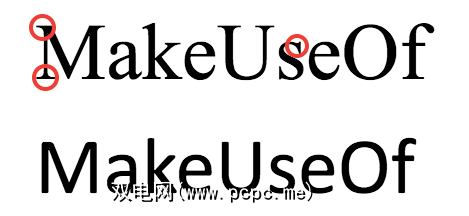
选择互补衬线和无衬线的最简单方法之一选择是将其保留在超家族中。 Viget提供了许多有用的超家族列表。这是确保您的衬线字体和无衬线字体相互补充的最简单方法之一。
您将很难找到一个专业的设计师,而该设计师不受制于这种排版的基本原则。如果要组合字体,则希望限制为两种或三种。
如果设计包含标题,子标题和正文,则可以使用三种不同的字体。如果您的设计不太注重文字,您可能只想坚持两个。
该规则有一些例外,但仅限于非常特殊的设计。
"在字体方面,“对立吸引"是绝对正确的。您不想使用过于相似的选项。它要么只是根本不会在您的设计中添加任何内容,要么看起来会略微有些瑕疵。
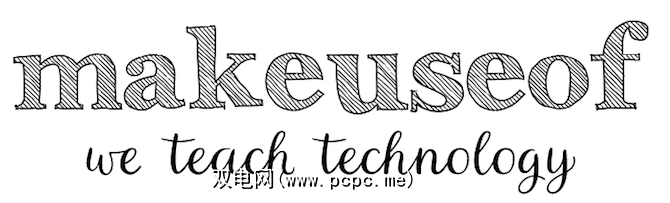
相反,请将漩涡状字体与粗体字体配对。将轻便通风的字体与粗字体配对。用优雅的草书选项将衬线字体连接起来。将平板衬线与手写字体选择选项配对,就像上面的示例一样。
查找灵感和想法
最后,如果您仍然发现配对字体的想法令人生畏,则可以有很多工具可以帮助您确保Calibri不会在人群拥挤的情况下运行。
Canva的Font Combinations可让您选择第一选择并就其合作伙伴的身份提出建议。 /p>
Typ.io的网站分为两个部分。第一部分以来自网络的字体组合为灵感来源:
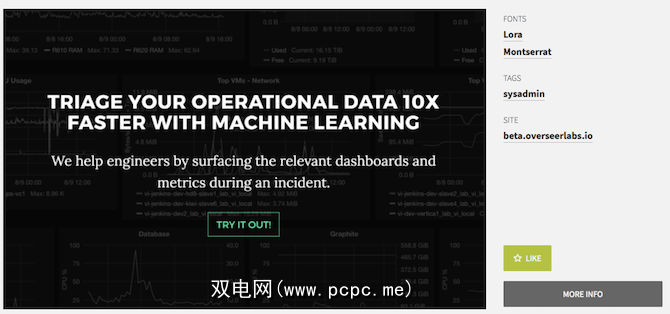
,另一部分以基于功能的字体配对得很好的字体列表为基础,例如是否将它们用于标题。或正文:
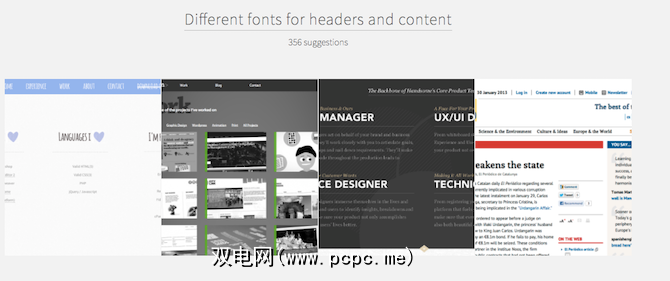
如果您发现自己在Adobe程序套件中进行设计,则“ Just My Type"将非常有用。该网站为Adobe的Typekit字体以及Hoefler&Co的Cloud Typography服务提供了配对建议。
Hoefler&Co.还提供了有关选择“字体调色板"的非常方便的指南,他们建议结合使用相同字体具有不同特征的历史时期或具有不同纹理的相似线质量。字体建议来自Hoefler&Co.,但您可以将规则应用于其他字体。
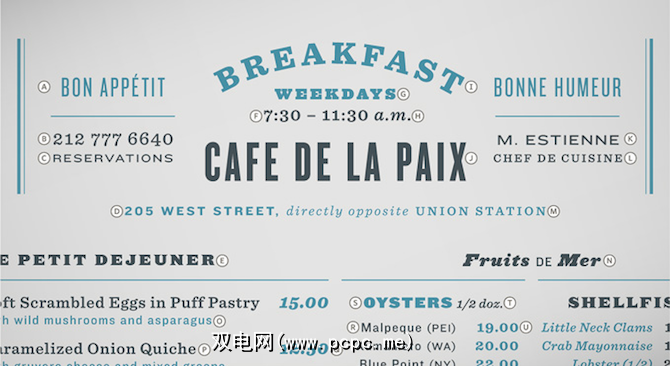
与大多数视觉效果一样,Pinterest是字体配对灵感的重要来源。只需搜索“字体配对"或“印刷术",您就会发现很多不错的建议:
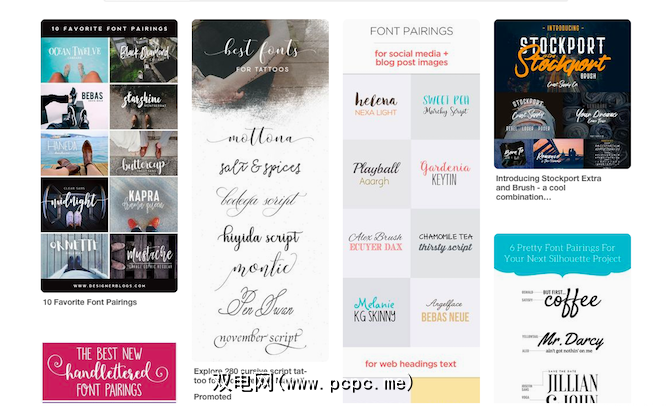
使用Type Connection配对字体。该网站使您可以选择第一种字体,而选择第二种字体则可以“选择自己的冒险经历"。
您是否想使用来自同一家族的相似字体,类似字体,对比字体,还是沉浸在过去?
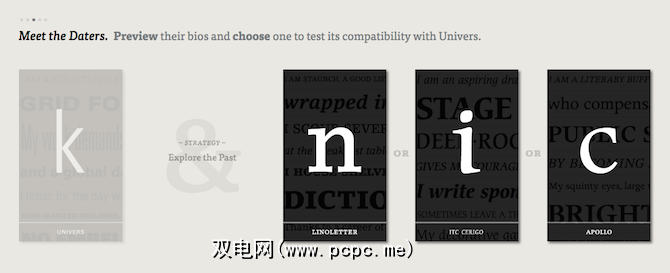
如果您选择的字体来源是Google字体,那么Google Type是这些字体如何完美搭配的绝佳灵感来源。该网站使用Aesop寓言中的文字和Unsplash中的照片,从视觉上启发了Google字体如何很好地协同工作。
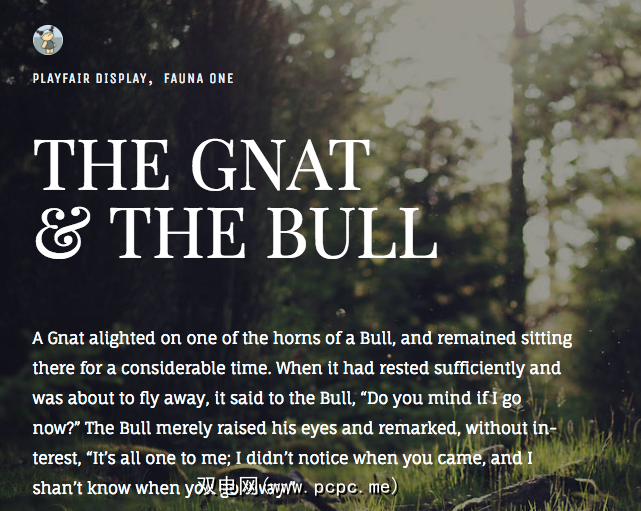
Font Pair是另一个适用于Google Web字体用户的便捷工具,为标题和正文提供了建议可以很好地配对的字体选择。
Typespiration不仅为您提供了如何组合字体的想法,而且还为您提供了很好的配色方案。
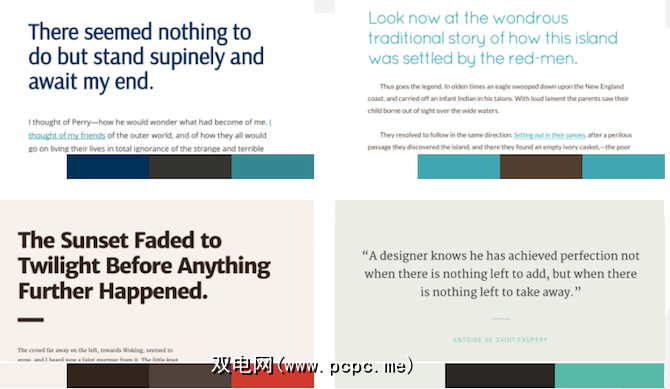
Web Font Blender不能使的建议,但它允许您使用不同的Google字体,并使用示例标题,副标题和正文文本进行预览。
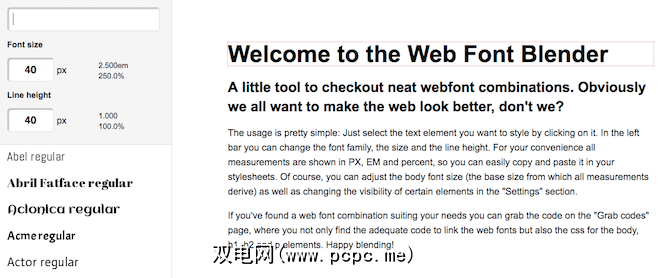
作为奖励,它会生成您需要使用的CSS这些字体是在线设计中的。